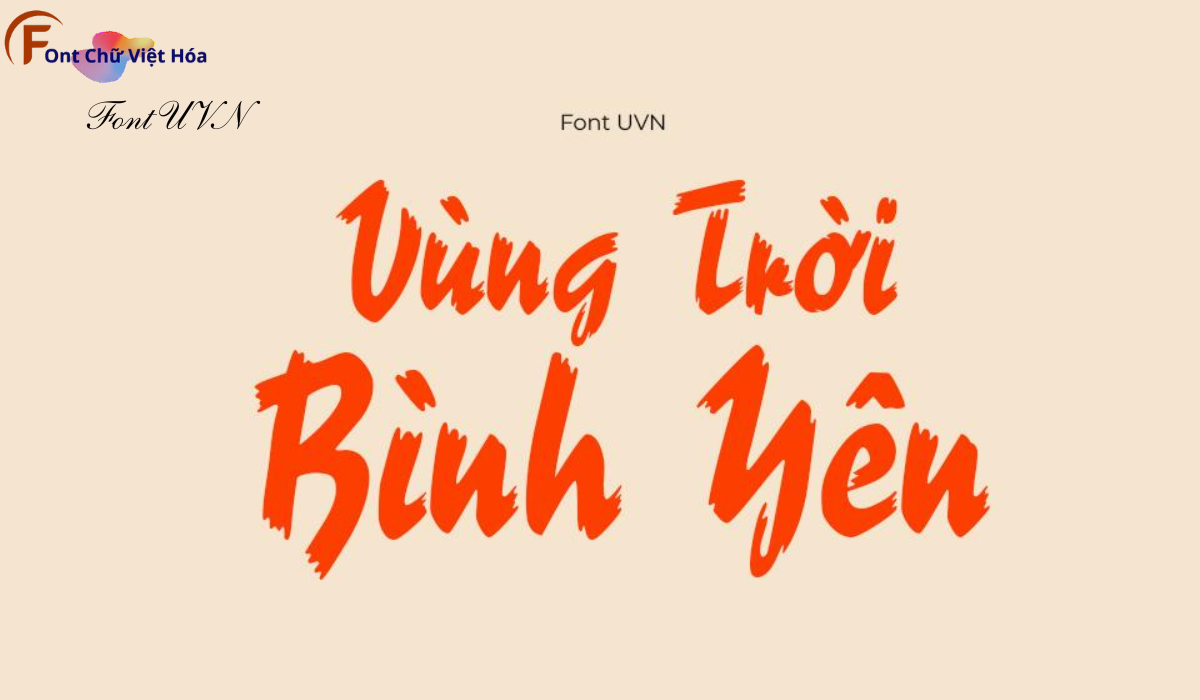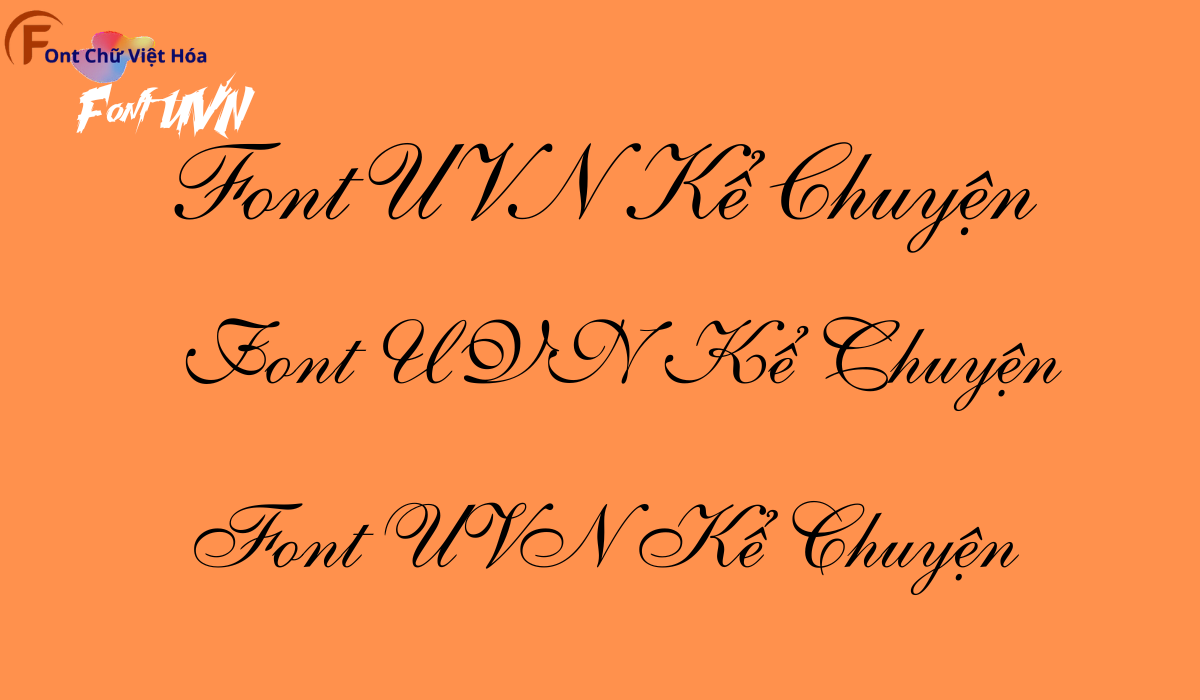
UVN Font Game Việt Hóa
Tác giả: UVN Font Game Việt Hóa
Bộ Font: UVN
Phân loại: Cá tính, Độc đáo
Kiểu chữ: Có chân
Độ dày: Thường, Đậm
UVN Font Game Việt Hóa là một font chữ không chân hiện đại, thuộc bộ font UVN. Được thiết kế với mục tiêu mang lại sự tinh tế và thanh lịch, font này phù hợp cho các dự án thiết kế như website, tài liệu, và bao bì sản phẩm. Với các nét chữ rõ ràng và độ dày đều đặn, UVN Font Game Việt Hóa không chỉ dễ đọc mà còn tạo cảm giác chuyên nghiệp. Việc Việt hóa font giúp người dùng dễ dàng sử dụng trong các thiết kế tiếng Việt, mang lại sự tiện lợi và thẩm mỹ cao.